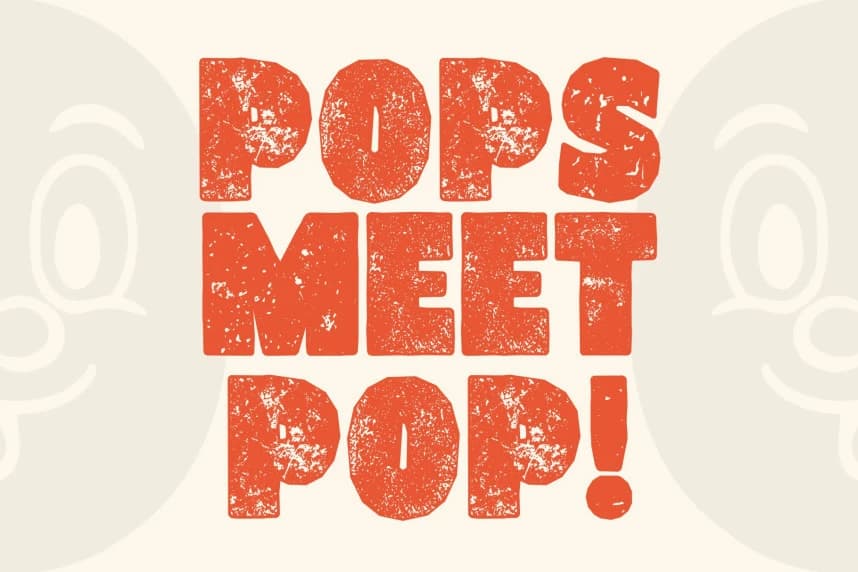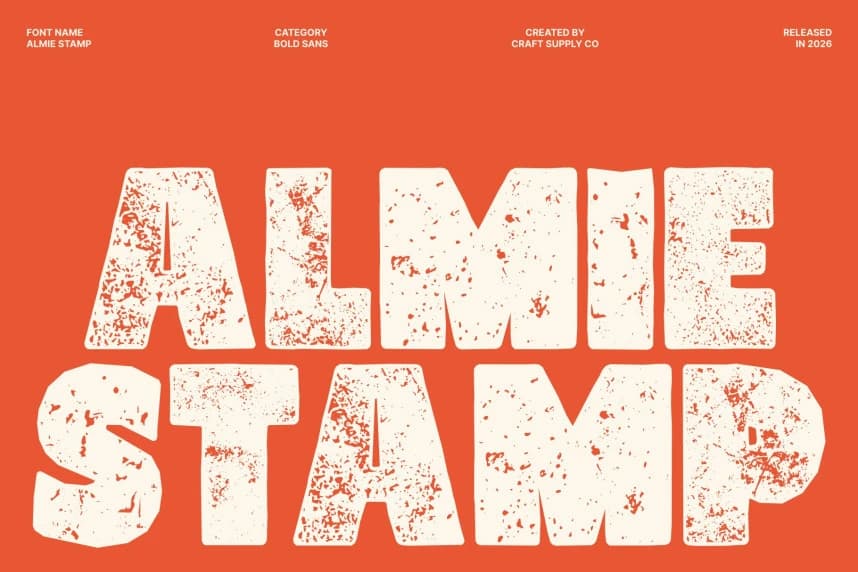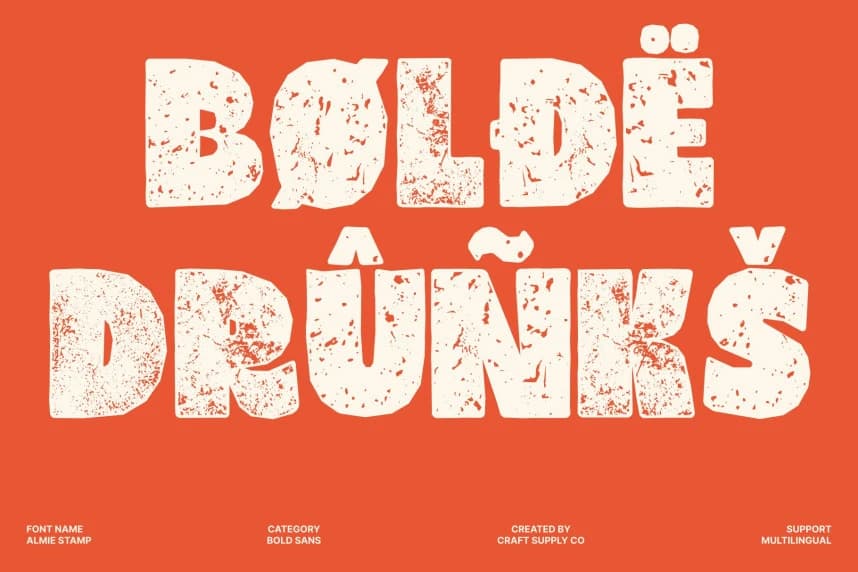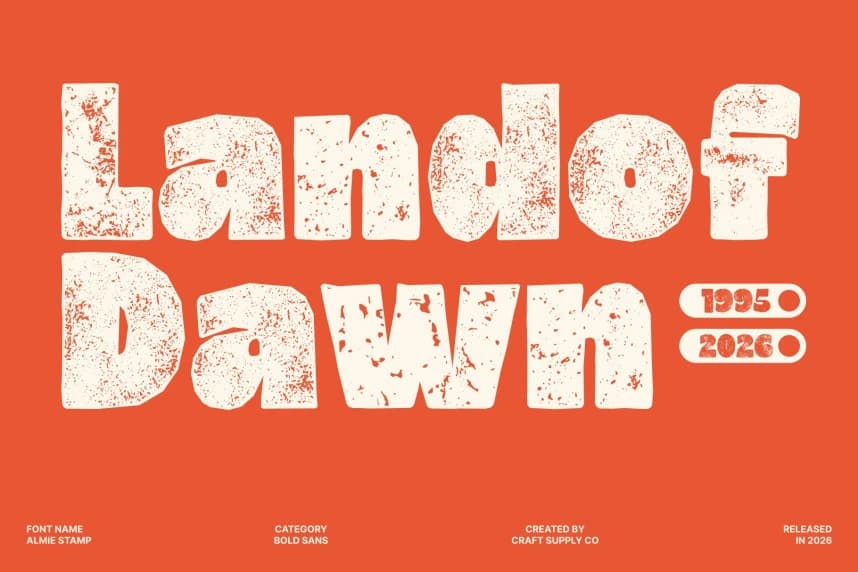
Almie Stamp Font – Bold ile Funk'ın Vintage Tavrını Buluşturan Font. Damgalı Kişiliğe Sahip Funky Bold Sans. Bu, funky enerjiyi ince damgalı dokuyla harmanlayan cesur bir sans serif fontudur.
Almie Stamp Font – Cesur ile Funk'ın Vintage Tavrıyla Buluşuyor. Funky Bold Sans, Damgalı Kişiliğe Sahip. Bu, funky enerjiyi ince bir damgalı doku ile harmanlayan kalın bir sans-serif yazı tipidir.